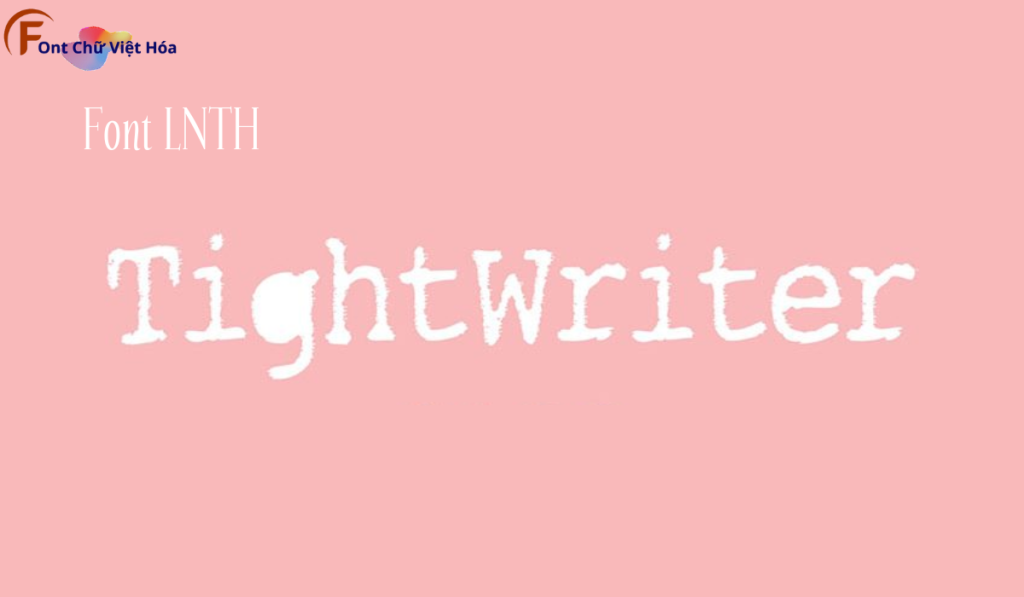
Font LNTH Tight Writer Việt Hóa
Font LNTH Tight Writer Việt Hóa là một font chữ cổ điển, thuộc bộ LNTH, với thiết kế như máy đánh chữ. Phong cách của font này phù hợp với các dự án thiết kế cần sự cổ điển và độc đáo, như bìa sách, thiệp mời, hoặc poster. Font LNTH Tight Writer Việt Hóa mang đến sự cổ điển và dễ nhận diện, ứng dụng trong các lĩnh vực sáng tạo. Đặc điểm hình dạng của font bao gồm các đường nét như máy đánh chữ, giúp tăng tính thẩm mỹ và sự chú ý. Việc Việt hóa font giúp người dùng dễ dàng sử dụng trong các thiết kế tiếng Việt, mang lại sự tiện lợi và linh hoạt.